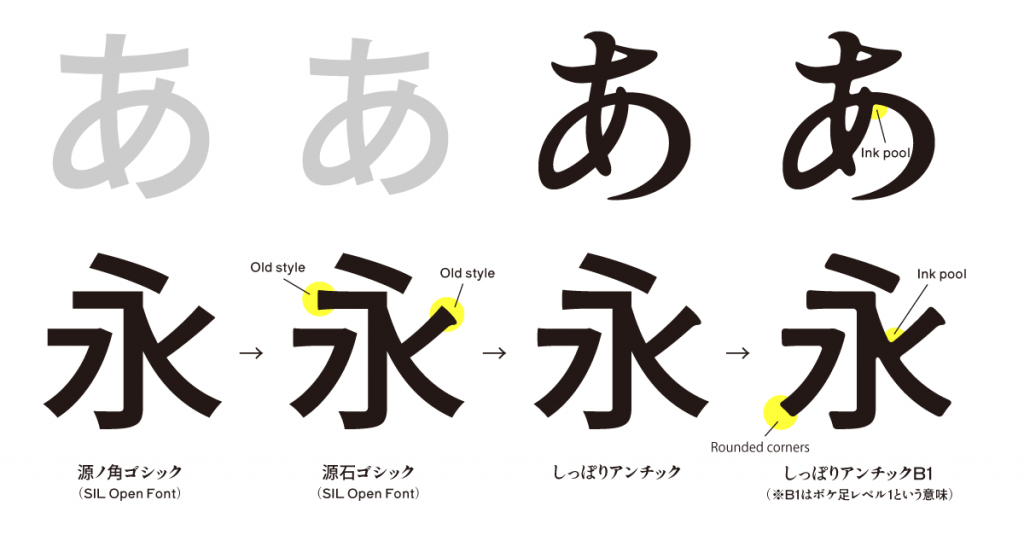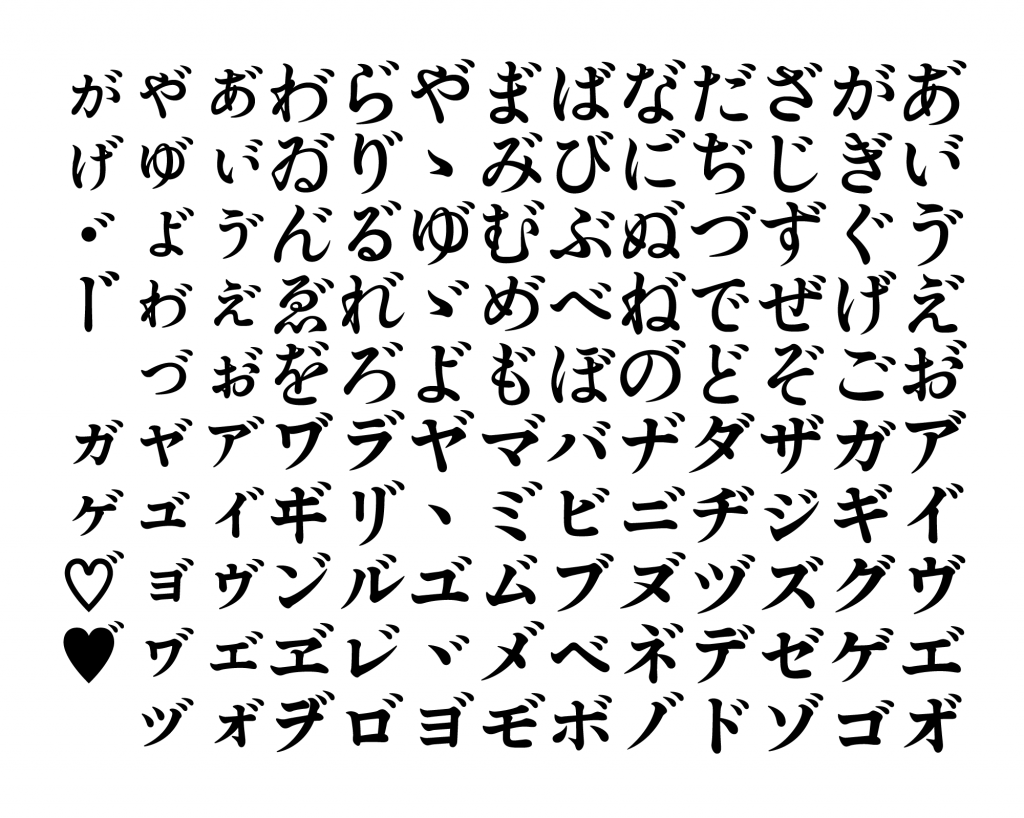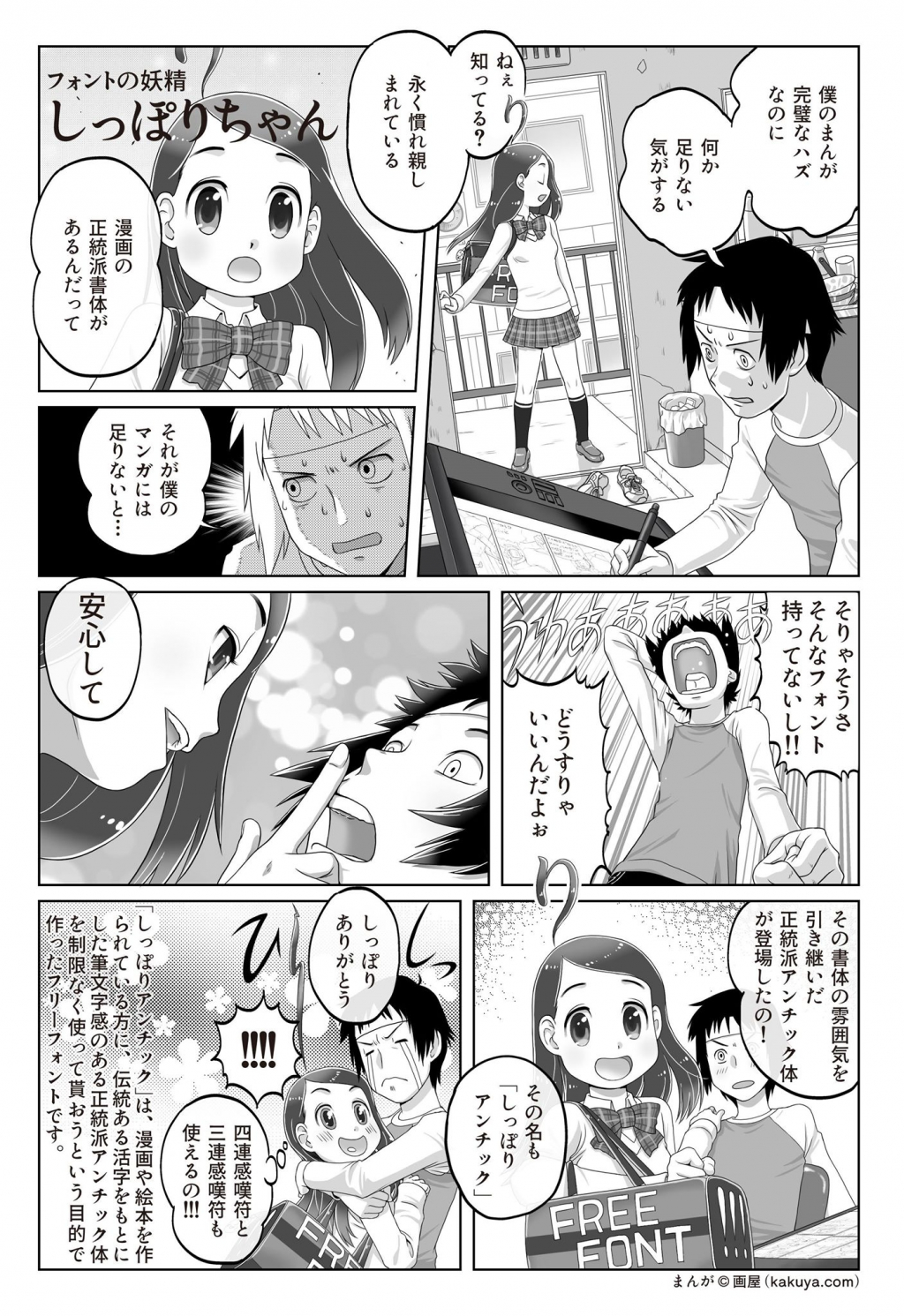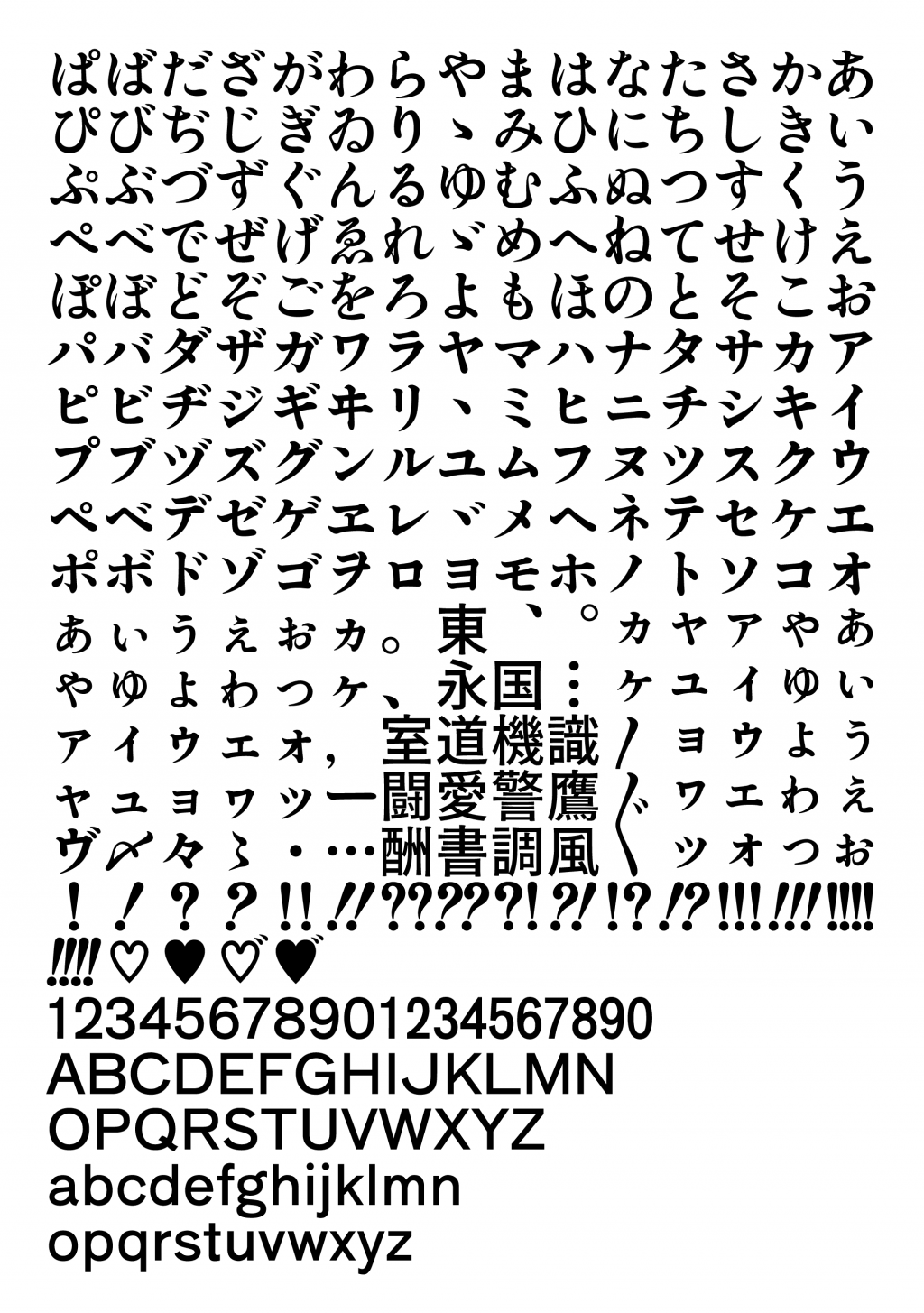
尾古是根据大正时代筑地体创作的“Shippori Mincho”结合厚实粘滞的假名和源石哥特汉字的漫画/漫画对话。这是最好的图画书免费字体句子。
我制作的目的是让制作同人志、漫画、漫画和图画书的人尽可能地使用基于传统印刷品的具有毛笔字感觉的正统古董机身。
在ver2.00中,记录了dakuten假名的添加,基本的ASCII+Latin-1字符的添加,以及SIL许可源石Gothic的汉字。
只有汉字包含 SIL 许可的 Source Han Sans Gothic(也是 SIL 许可的 Source Han Sans 的衍生字体)。
我们还制作了一个名为 Tail Antic B1 的版本,其中人物的边缘更加模糊。
我们与同人作品需要的dakuten一起录制了假名。
您可以通过在要打开浊音的浊音(例如“A”)旁边输入浊音“”(U + 3099)来获取它,但根据应用程序可能无法正确显示. 在这种情况下,从字形调色板输入。